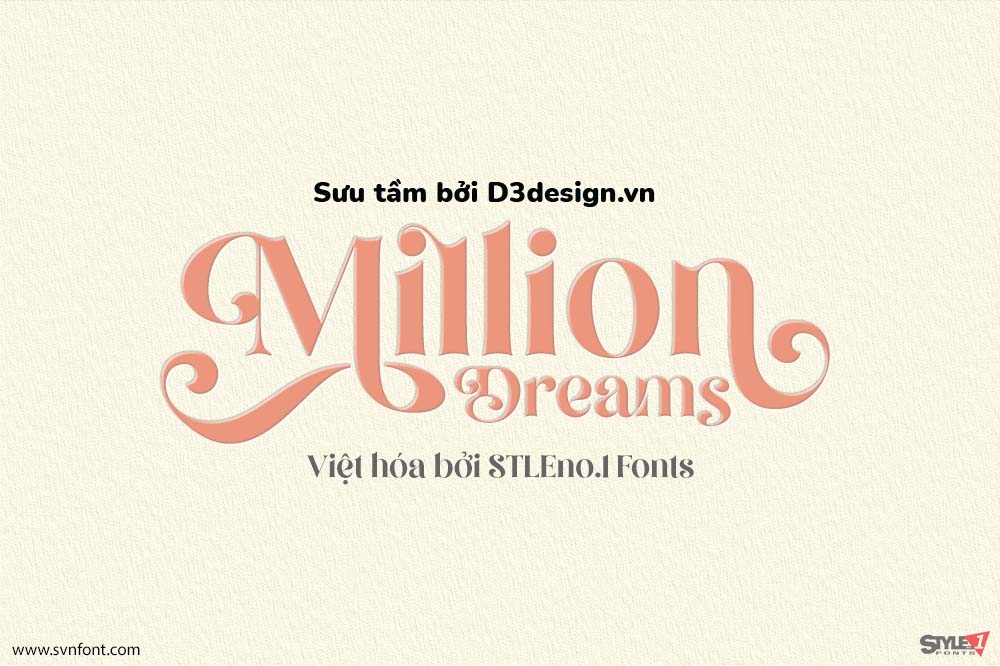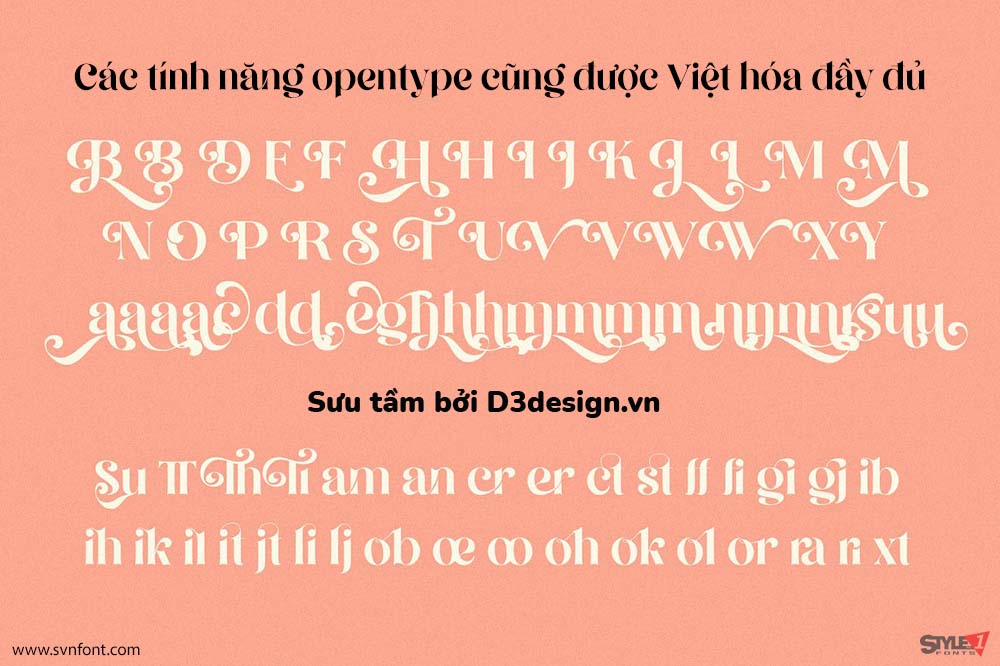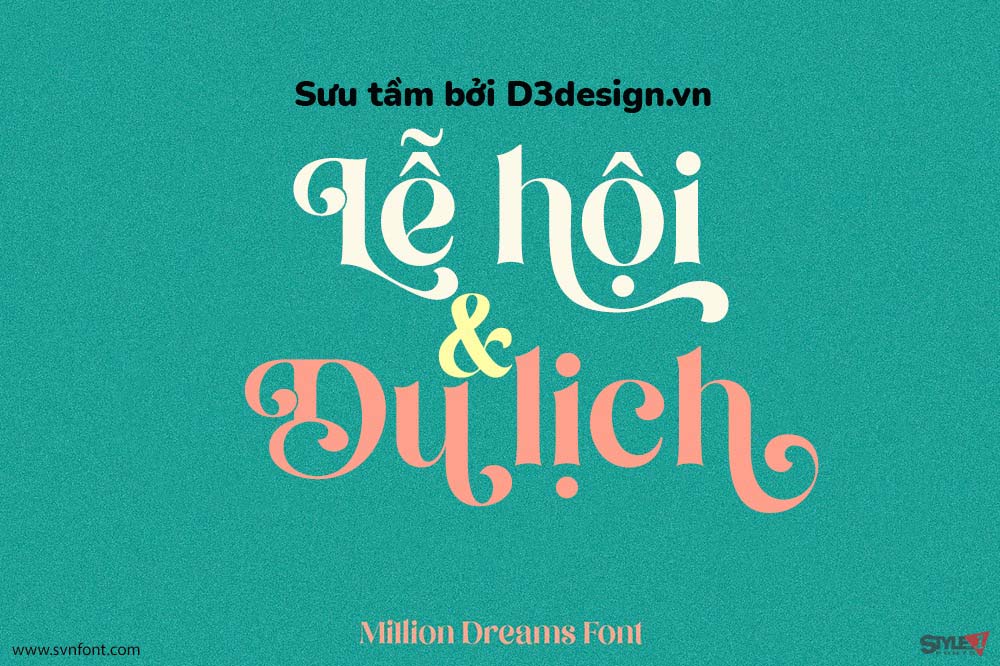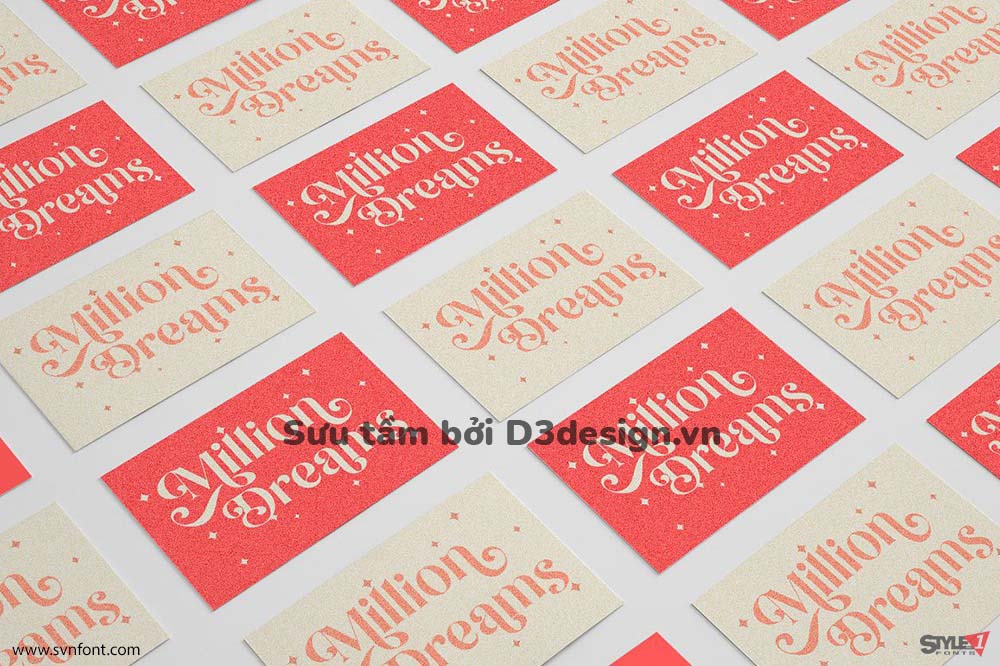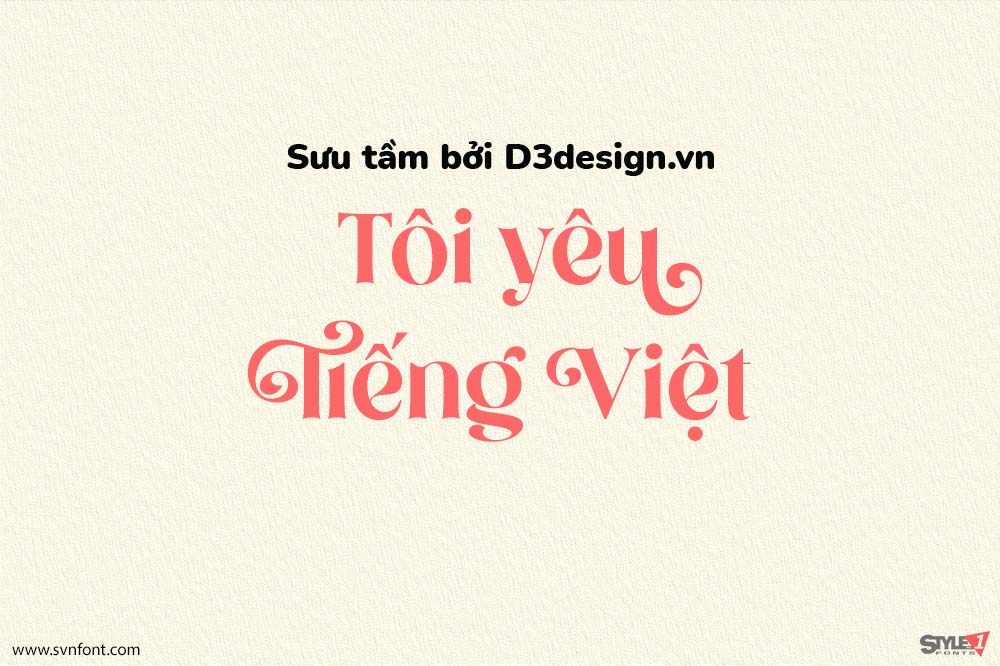
Font Việt Hóa SVN- Million Dreams Phong Cách Vui Tươi, Nữ Tính
Million Dreams - một font mang phong cách vui nhộn, tuổi thơ và nữ tính. Với nhiều kiểu ký tự thay thế, ký tự ghép cũng được Việt hóa, mang lại nhiều tính năng kết hợp hoàn hảo cho sự sáng tạo của bạn.
Nhà thiết kế: INKSUN
Nhà phát hành: INKSUN
Việt hóa: STYLEno.1 Fonts